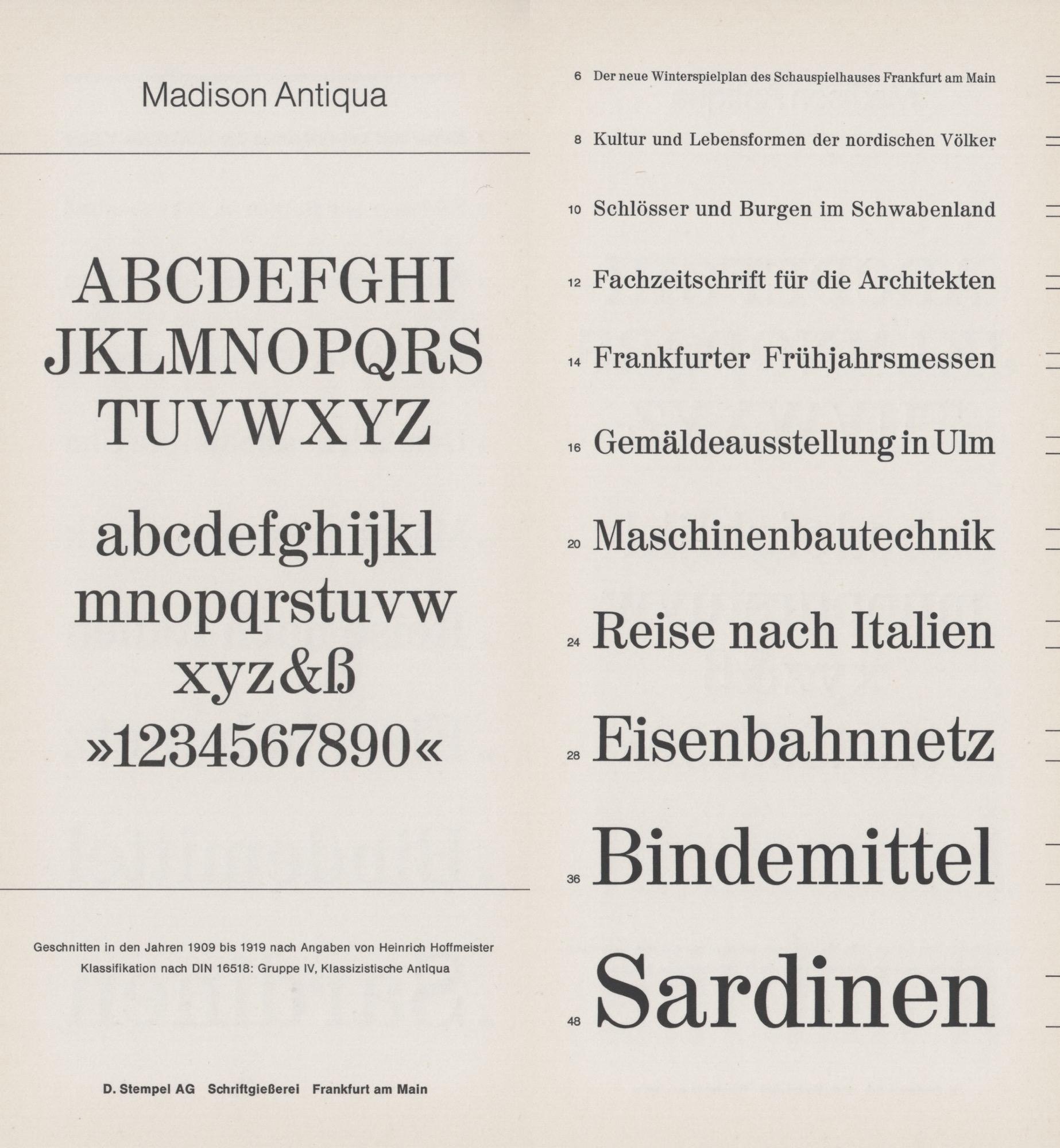
• circa 1965
• Serifen:
• serif
• Antiqua statisch
Die Madison-Antiqua ist eine Neuveröffentlichung der Anfang des 20. Jahrhunderts erschienenen Amts-Antiqua von Heinrich Hoffmeister. Eine digitale Version in fünf Schnitten (normal, kursiv, fett, schmal, schmalfett) ist heute über Linotype erhältlich.